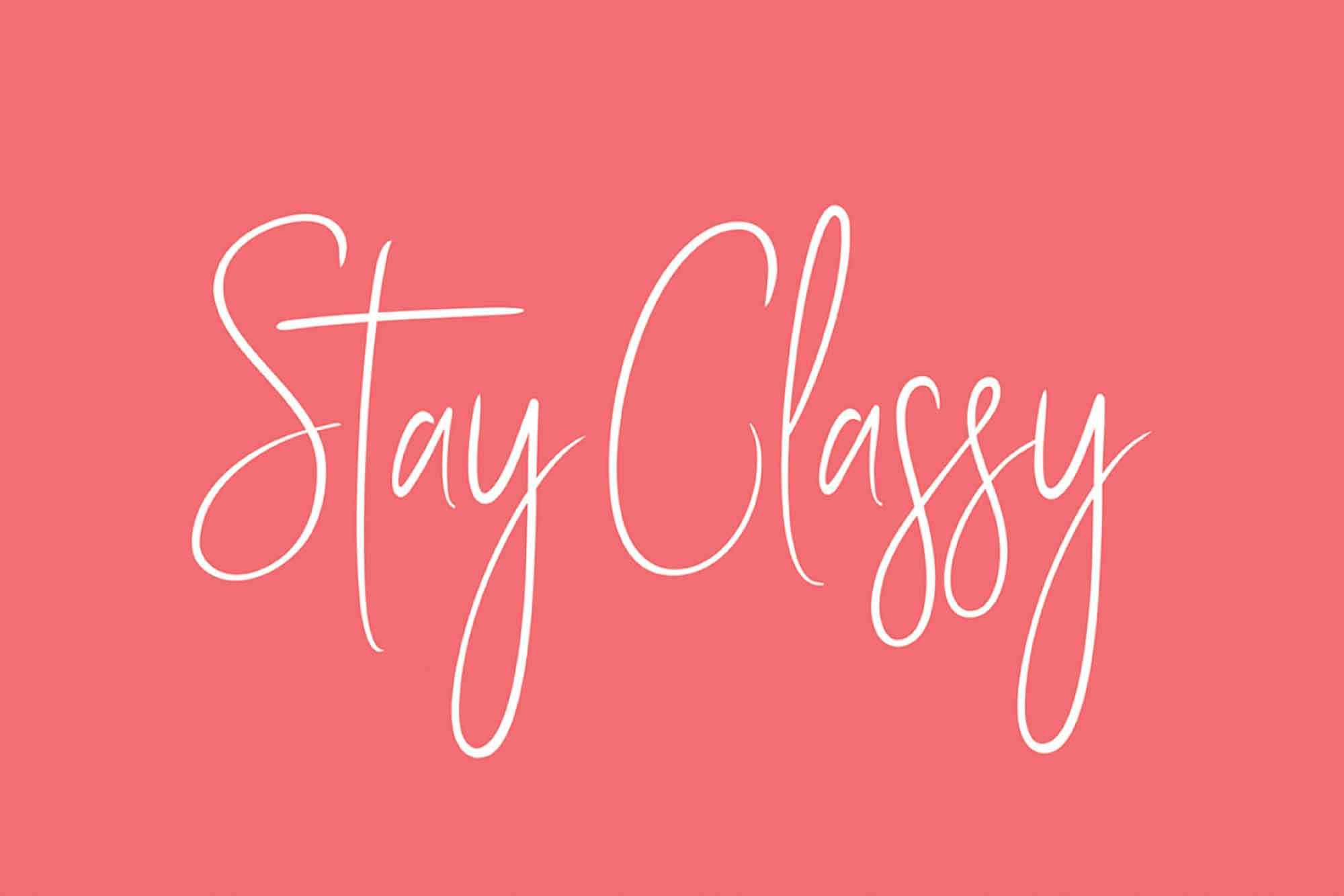
Free Stay Classy Script Font – Download Grátis
A fonte “Free Stay Classy Script Font” é uma seleção elegante e personalizada para quem busca um touch de charme em suas mídias gráficas. As fontes de estilo script têm o poder de transformar qualquer design em um elemento de destaque, especialmente quando combinadas com uma paleta de paletas de cores que destacam o texto. Suas linhas fluidas e curvas delicadas, que imitam o estilo da escrita a mão, não só dão um toque artesanal a qualquer design, mas também criam uma conexão única entre sua marca e o seu público. Quando usada, esta fonte convida à personalidade e à experiência de um diálogo íntimo, como se o texto fosse escrito especialmente para a pessoa que recebeu. Escolher um estilo de tipo que parece ter sido escrito a mão traz uma sensação de conexão ímpar, ajudando a estabelecer uma relação mais próxima com seu público alvo, especialmente em mídias como cartazes, diretivas de marketing impressas ou materiais de divulgação. Em um mundo digital cada vez mais ruidoso, o uso desta fonte pode fazer com que seu recurso gráfico se destaque, fazendo com que seus esforços de marketing sejam memoráveis e eficazes.